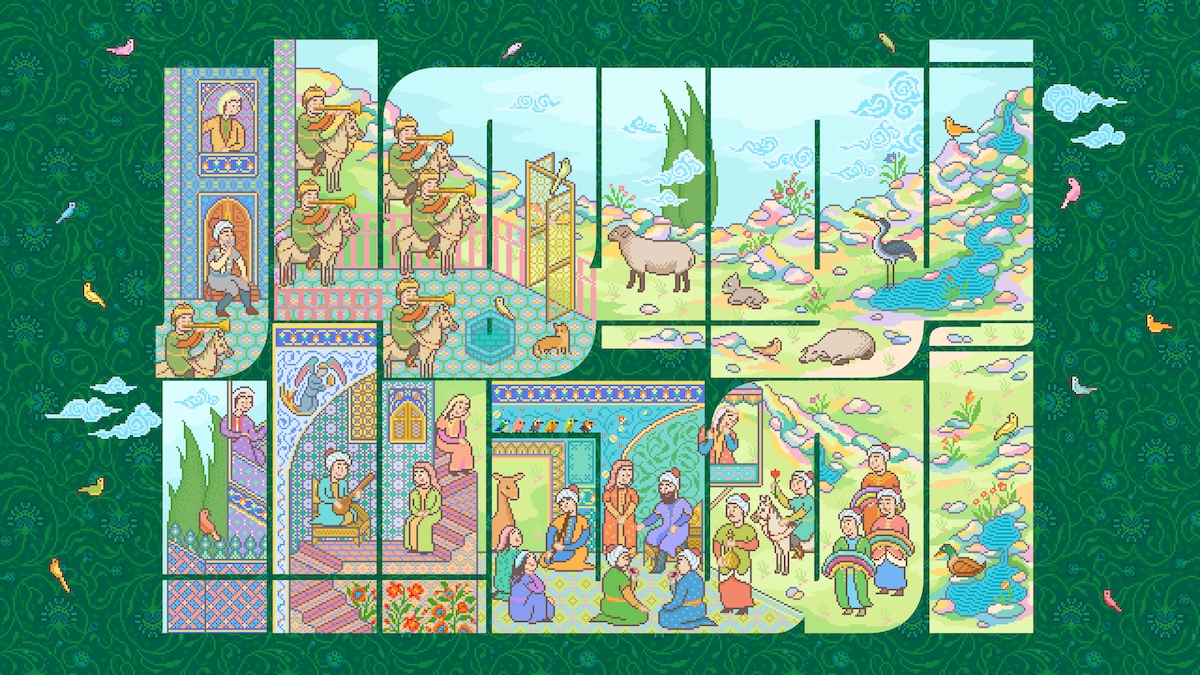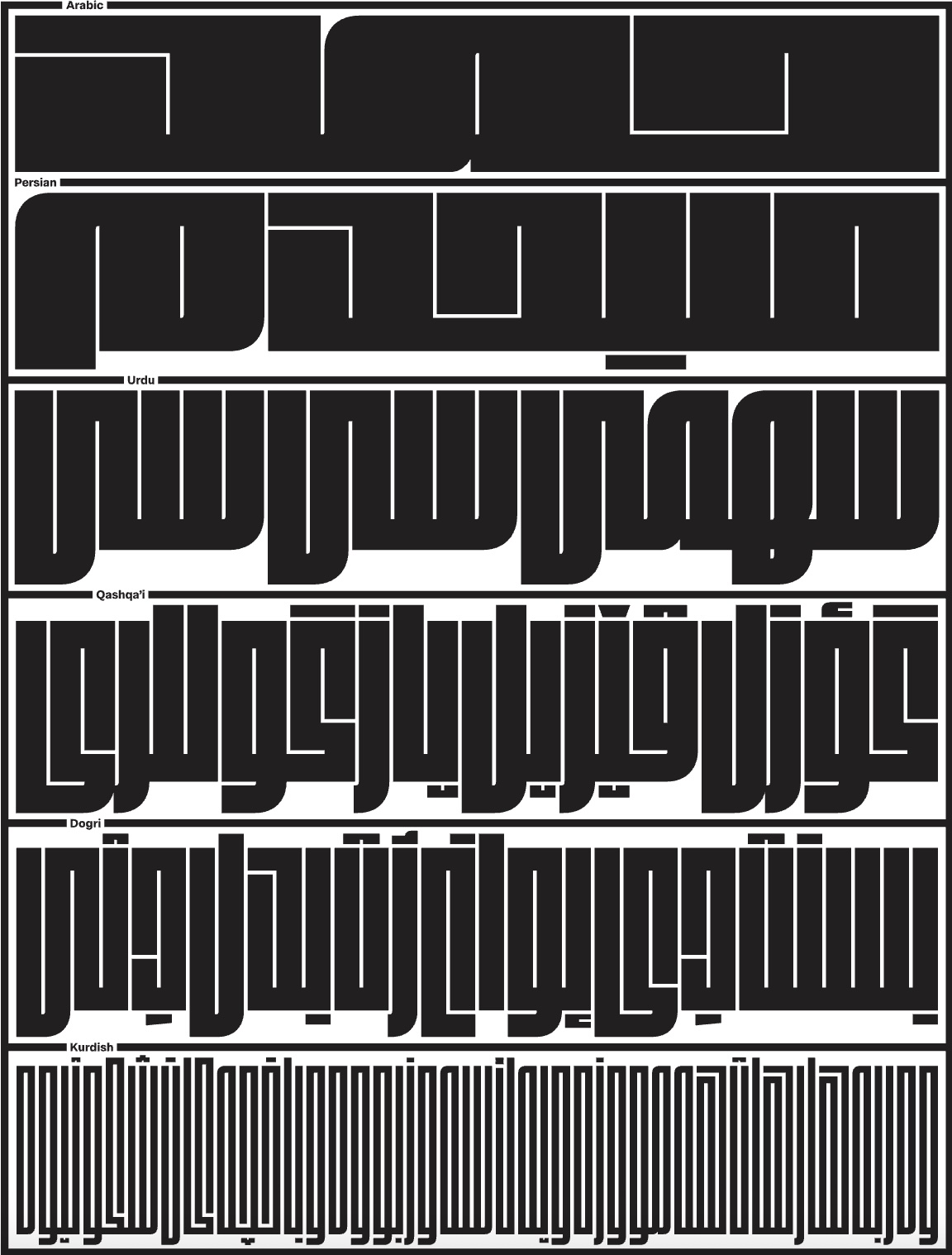
Was entstehen kann, wenn man miteinander kollaboriert, zeigt die Londoner Dogray Foundry, die mit der Fit Arabic eine spannende kalligrafische Adaption der Fit des US-Typografen David Jonathan Ross vorstellt.
Fit Arabic von Dogray Type Foundry mit einer Illustration von Naime Pakniyat
Lange haben Sahar Afshar und José Solé in London in großen Foundrys gearbeitet, doch das Gefühl gehabt, den Kontakt zur Community zu verlieren.
Deshalb haben sie ihre Dogray Type Foundry gegründet und legen seither umso größeren Wert auf die Zusammenarbeit mit anderen, auf den Austausch mit der Design-Community – und auf besondere Schriften.
»Wir sind überzeugt, dass die beste Arbeit entsteht, wenn unique und diverse Perspektiven aufeinanderprallen«, sagen die beiden.
Und das zeigt sich auch mit ihrer neuesten Schrift Fit Arabic.
Kollaboration im Mittelpunkt
Die Fit stammt von dem preisgekrönten TypografenDavid Jonathan Ross aus Los Angeles, der mit der Fit eine hyperstilisierte Schriftfamilie entwickelte, die ganz auf ihre Flächenwirkung ausgerichtet ist.
Um das zu erreichen, wurde Fit als variable Schrift mit einer außergewöhnlich großen Bandbreite an Breiten angelegt und zeigt sich in extrem schmalen und nahezu absurd breiten Varianten – wobei ihre Punzen, ihre Zwischenräume, immer gleich bleiben.
2017 hat Ross die Fit gezeichnet, von Oded Ezer wurde sie ins Hebräische erweitert, von Gor Jihanian ins Armenische. Sie liegt zudem in Devanagari, adaptiert von Kimya Gandhi und in Tamil von Aadarsh Rajan vor.
Dogray Type aus London haben die Fit jetzt ins Arabische übertragen. Und das mit einem zusätzlichen Twist, da sie die Fit in der geometrischen Kalligrafie der Kufi, eine der ältesten Schriftarten des Islam, übertragen haben.
Gleichzeitig haben sie die Geometrie auch mit Rundungen und dazu mit wunderbaren Illustrationen von der iranischen Pixel-Künstlerin Naime Pakniyat in Szene gesetzt.
Eine gleich dreifache Kollaboration war es also sozusagen und das mit einem umwerfend schönen und spannendem Output.